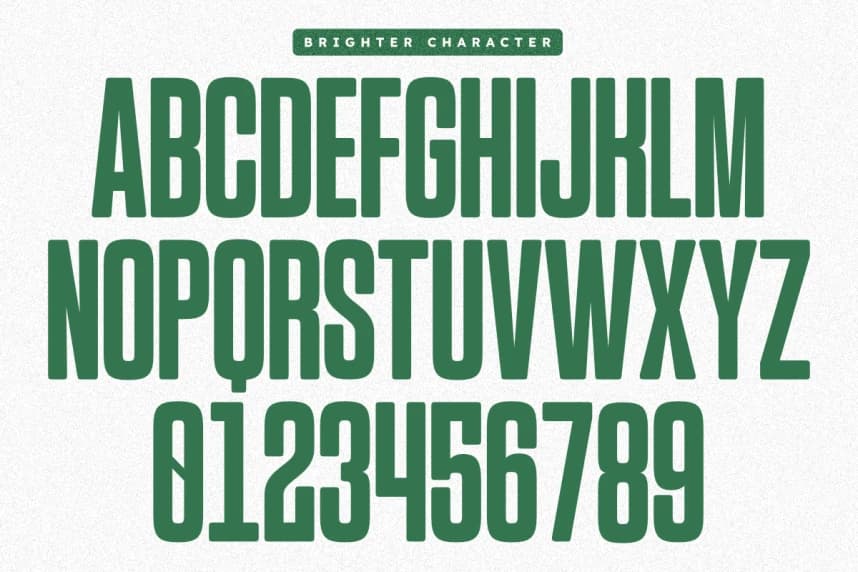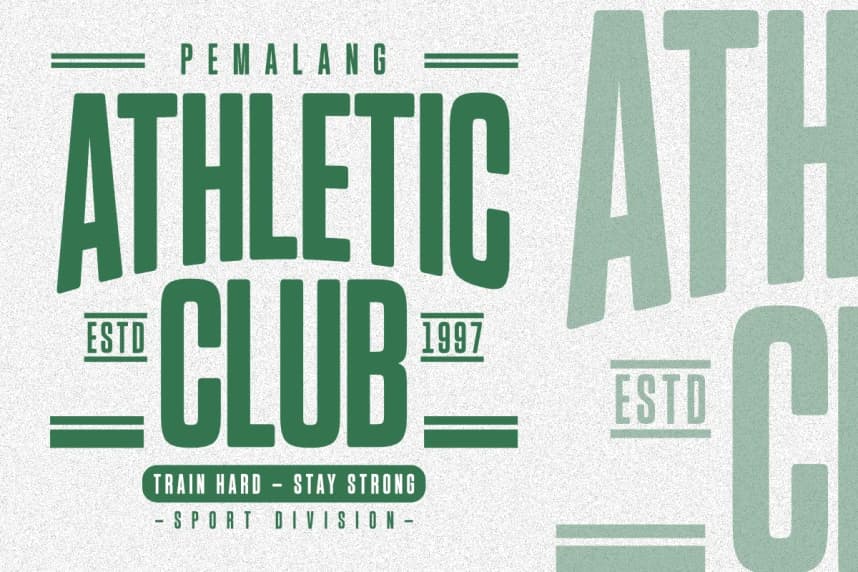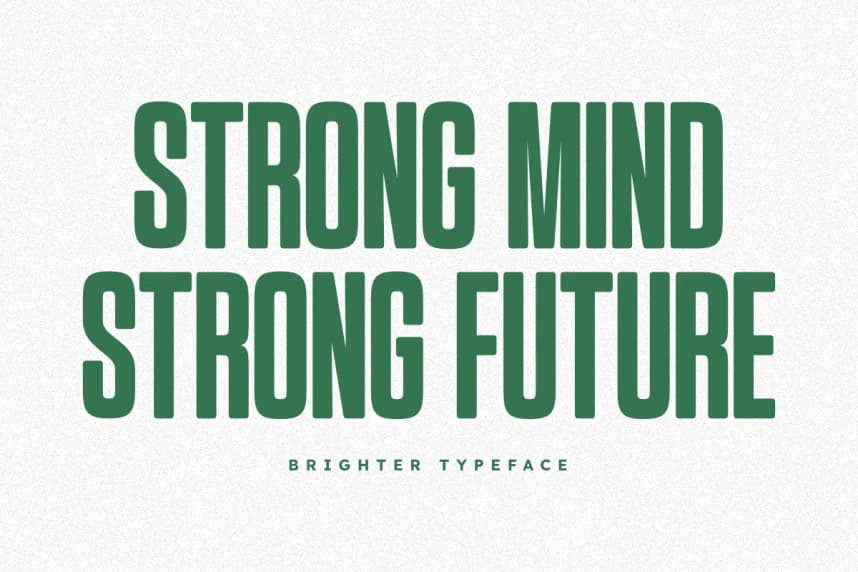
Daha Parlak Sans-Serif Yazı Tipi
Brighter Sans Serif Font, cesur ve çok yönlü bir retro sans serif yazı tipidir; geçmişin estetiğinin nostaljik çekiciliğini zahmetsizce yakalarken temiz ve modern bir hava korur. Uzun ve sağlam bir yapıya sahip olacak şekilde tasarlanan bu yazı tipi dikkat çeker.
Brighter Sans Serif Font, cesur ve çok yönlü bir retro sans-serif fontudur ve eski estetiğin nostaljik çekiciliğini zahmetsizce yakalarken temiz, modern bir dokunuşa sahip olur. Uzun ve sağlam bir yapıya sahip olarak tasarlanan bu yazı tipi dikkatleri üzerine çeker.